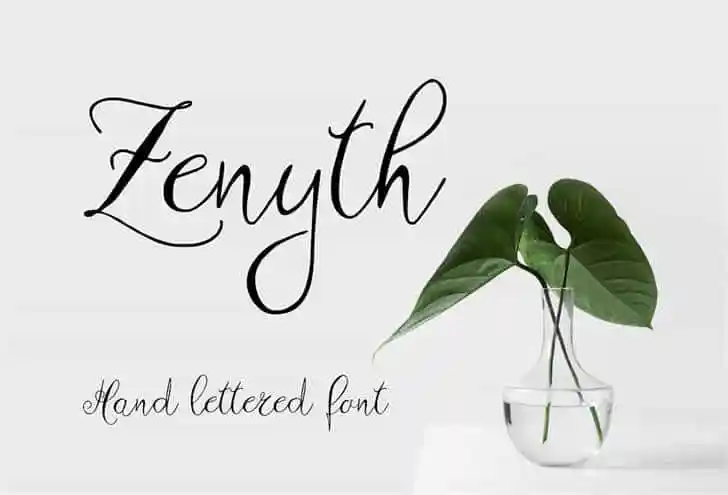
Zenyth Script Font
Zenyth Script Font é uma fonte que traz a essência do autêntico traçado pela mão, ideal para projetos que valorizam um toque pessoal e natural. Esta fonte foi criada por Hamilton e desenhe de forma única, introduzindo-nos ao mundo da escrita em estilo script. Com suas letras minúsculas, maiúsculas, números, símbolos de pontuação e moedas, Zenyth Script Font é uma escolha versátil para diversas aplicações gráficas. Seja você um designer de embalagens ou editor de design editorial, Zenyth Script Font oferece a oportunidade perfeita para criar designs que expressam originalidade e personalização. Suas linhas suaves e elegantes se encaixam em qualquer tipo de projeto: desde os elementos da estação de casamento e embalagens de produto até os decoupage de parede e design de marca, Zenyth Script Font é uma escolha conveniente para qualquer aplicação visual. Além disso, essa fonte pode ser usada como um overlay textual sobre qualquer imagem de fundo, tornando-a flexível e adaptável a diferentes ambientes gráficos. É perfeita para quem quer dar vida à sua arte com o toque autêntico da escrita em script, seja para uma apresentação de projeto, cartazes publicitários ou até mesmo para criar um design de marca inovador. Zenyth Script Font é um recurso atraente e versátil que irá transformar seus projetos digitais com o toque pessoal que você busca.